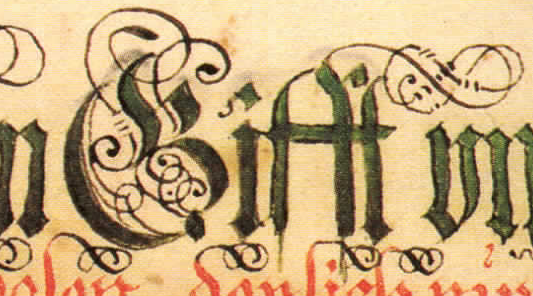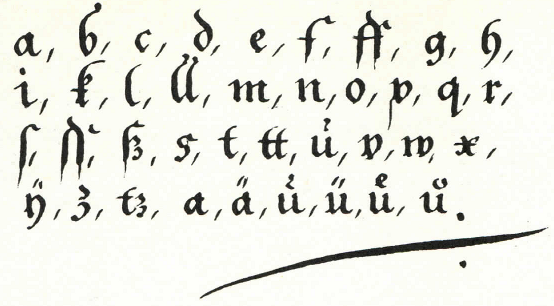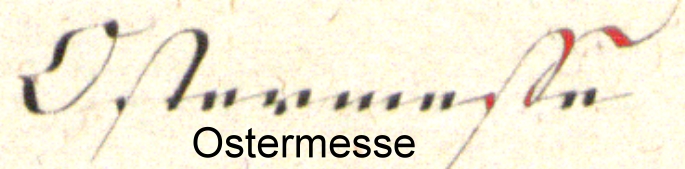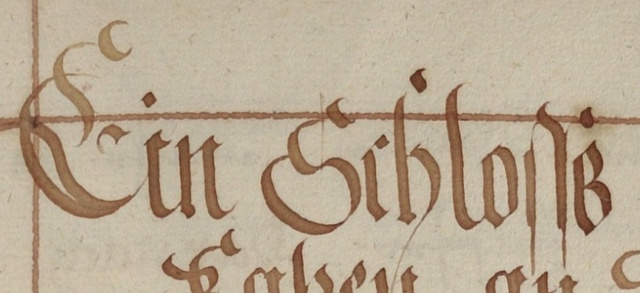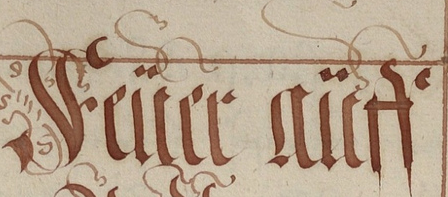
Das bei ›Schloſſs‹ ist ein Schluss-s – quasi in der Form des Versal-Fraktur-S.
Da scheint einer gerne Doppelungen gedoppelt zu haben (ü + e, etc.).
Das Rund-s ist klar, aber diese Doppel(?)-ſ-Konstruktion, die die so seltsam verbunden ist und in der beide Zeichen jeweils unterschiedlich gestaltet sind, hab ich so noch nie gesehen.
Und Schloſſs mit dann drei s – oha! Muss ja ein besonders scharfes Schloss sein. ;-)
Da scheint einer gerne Doppelungen gedoppelt zu haben (ü + e, etc.).
Da steht aber nicht ü + e, sondern nur u + e, das da über dem u ist dieses Häkchen, dass man zur Unterscheidung zum sonst gleich geschriebenen n drüber gesetzt hat, hier wie eine Tilde geschrieben.
Auch solche ſſ-Ligaturen, mit unterschiedlichen Formen für die beiden ſ war durchaus üblich.Ostermesse.jpg
Da steht aber nicht ü + e, sondern nur u + e, das da über dem u ist dieses Häkchen, dass man zur Unterscheidung zum sonst gleich geschriebenen n drüber gesetzt hat, hier wie eine Tilde geschrieben.
Das ist bei Kurrentschriften wie deiner Ostermesse so, aber bei anderen gebrochenen Schriften (und dem Beispiel oben) sehe ich einen deutlichen Unterschied zwischen n und u – und eine Tilde sieht auch anders aus  :-?